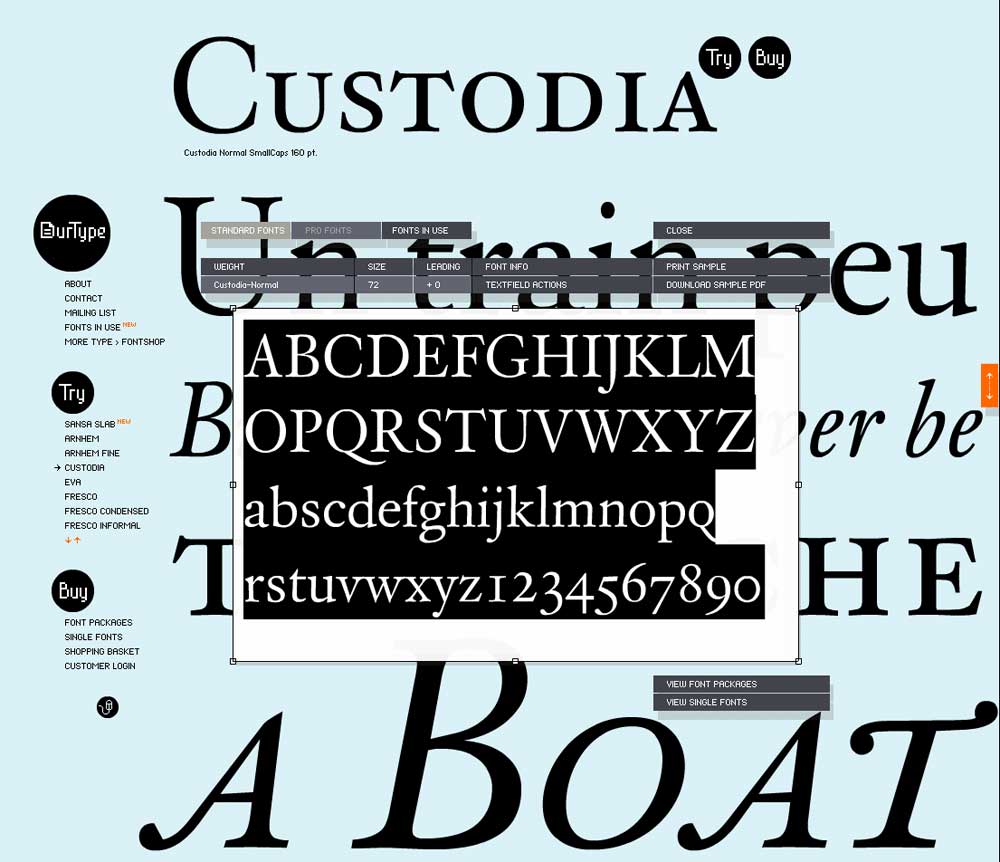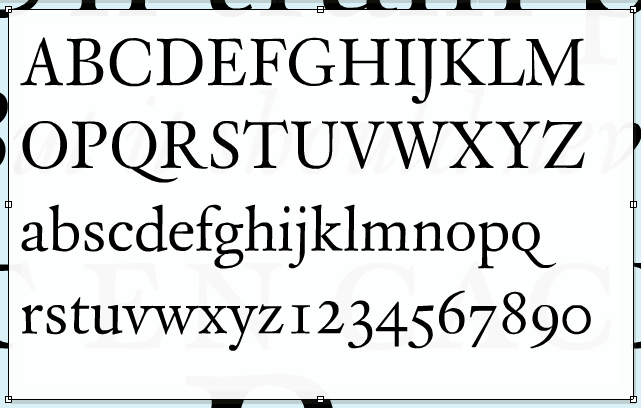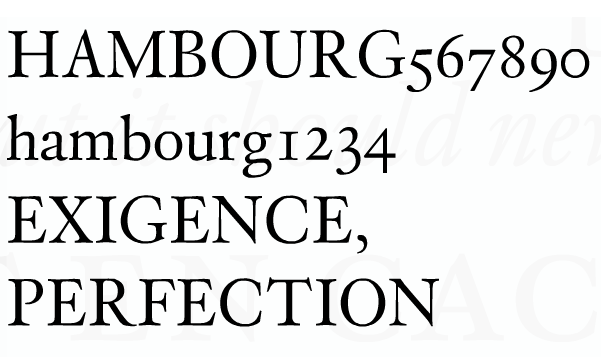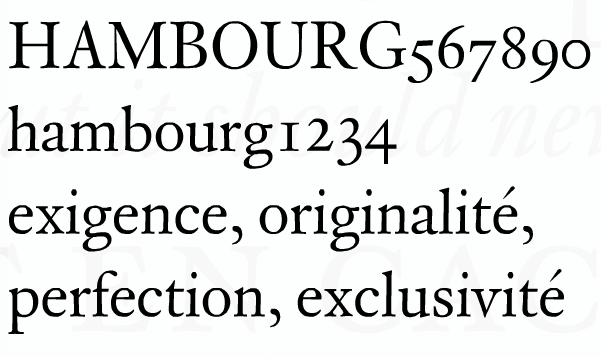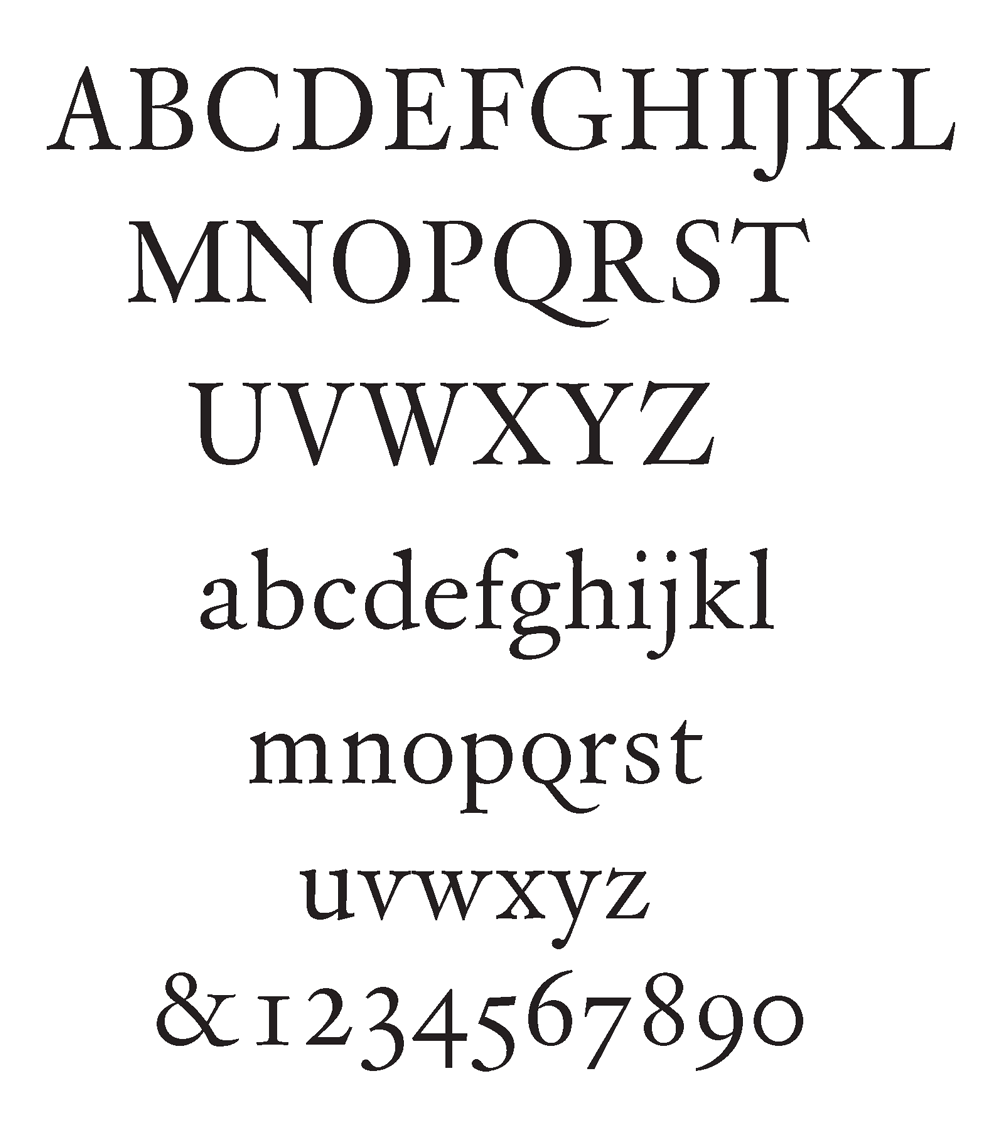
typographie introuvable
Une agence m’a demandé de retravailler un logo en partant de cette typo… je n’arrive pas à le retrouver dans aucun catalogue… quelqu’un pourraît-il(elle) m’aider. Thanks.
l’agence m’a envoyé une planche d’alphabet plus complète… je viens de passer en revue quelques 10000 polices chez FontShop, je n’ai tjrs rien trouvé… bizarre tout de même…
Alors pour simplifier j’ai réuni les deux billets:
OurType et le Custodia similar to Van Dijck
Le caractère cherché était le Custodia de la Fonderie OurType.be.
Voici quelques années, cela remonte quand même à la décennie 70, Mattew Carter et Mike Parker avait monté une entreprise devenu célèbre depuis, Bitstream. A l’origine, avec l’aide de Charles BIGELOW me semble-t-il ces entrepreneurs avaient pour purpose de fournir à la société Scitex une collection complète de fontes digitales qui allait permettre à un fabricant d’ordinateurs de photogravure d’inclure la typographie vectorielle à leur montage numérique. Nous étions au milieu des années 70… eh oui le numérique n’est pas né en 1989 avec l’arrivée du PostScript©.
Pour réduire le coût désastreux des royalties à payer aux ayants droits des polices originales*, Mattew Carter a décidé avec ses associés de procéder à un pillage en règle des polices les plus connues de l’époque. Le procédé était simple, on changeait quelques formes, on renommait les polices et on diffusait. La loi américaine sur le copyright ne protégeant que le nom des polices, ils se mettaient en conformité en usant de noms d’emprunts tel le Swiss pour l’Helvetica ou l’Humanist pour le Gill Sans… Au sein de l’ATYPI (association typographique internationale) personne n’a moufté, John Dreyfus lui-même était désolé de ces dérives qui allaient à rebours de tout le combat qu’il avait initié avec Charles Peignot dans les années 60… Mais l’ATYPI était alors en grande partie financée par les industriels des Arts Graphiques qui s’entendaient par dessus des intérêts des dessinateurs. Autant dire que lorsqu’ITC a démarré en 1970 ils avaient fort à faire pour rester dans la course à la création des polices qui nécessitait tout de même d’autres invesitssements à l’époque que les petites mains d’un designer d’aujourd’hui équipé de FontLab et d’un powerbook intel connecté à un grand écran.
Je poursuivrai prochainement ce billet avec des exemples concrets mais je vous invite à découvrir les derniers avatars de cette époque lointaine avec le Custodia qui est un magnifique plagiat du Van Dijck de la fonderie Monotype… Le monde de la typographie est aussi cruel que celui de Dallas, j’en ai vécu quelques séquences ;-)
* pas même sûr que les sociétés détentrices des droits auraient donné leur accord, tant la guerre entre fabricants de machines à composer faisait rage à travers le monde.
Suite et précisions de Jonathan Munn concernant le concept de plagiat…
» tu sais l’un des gars qui a monté le FontShop belge… on peut se poser des questions… pas vrai?  »
?????
Quelle questions ?
Il est ou le problème ?
De quelle manipulation machiavélique s’agit t’il?